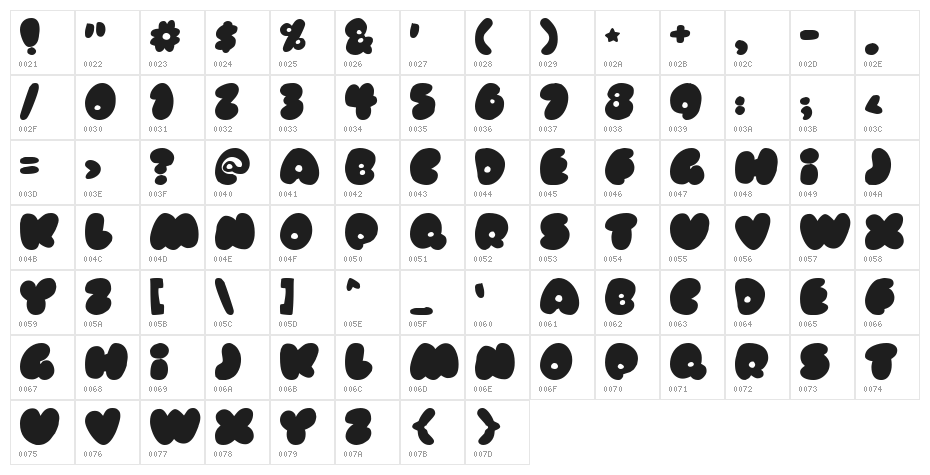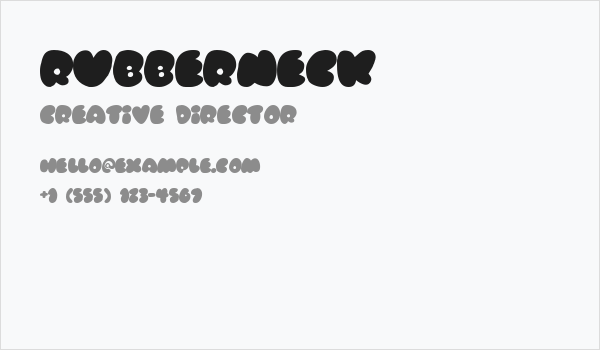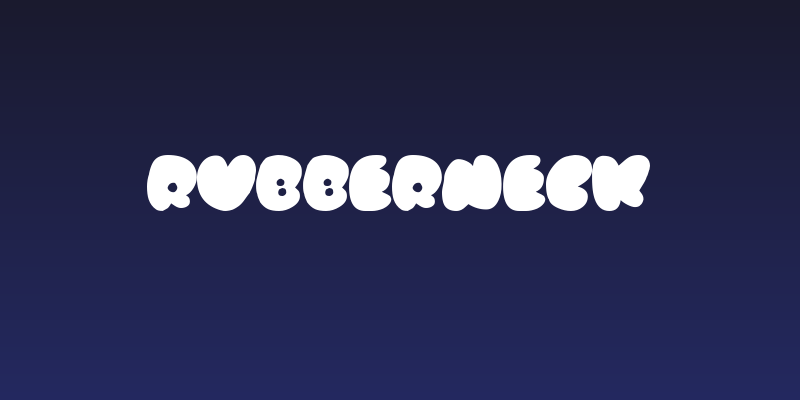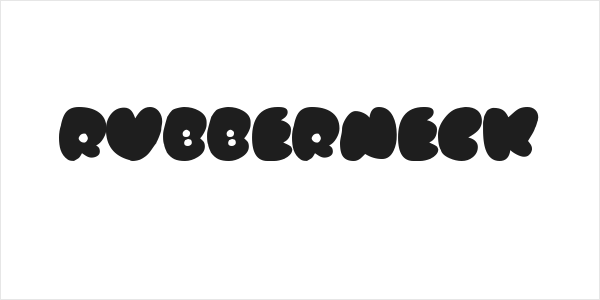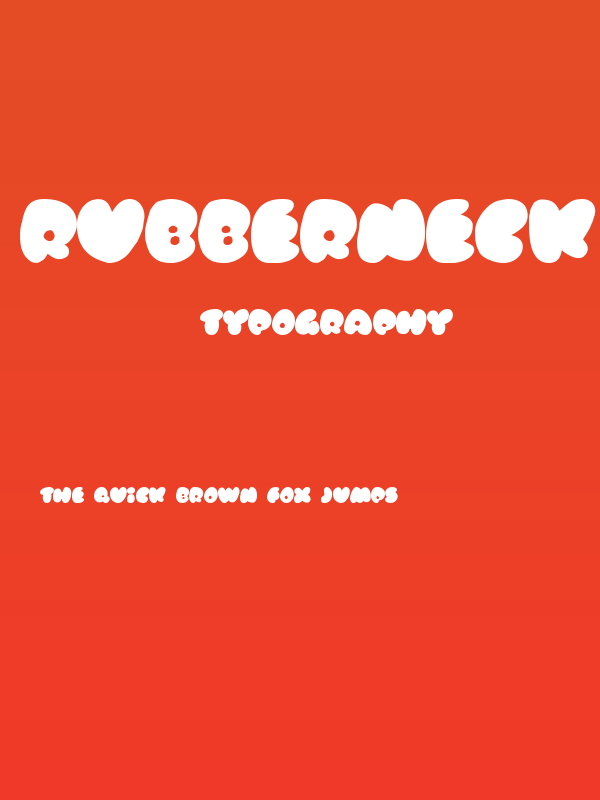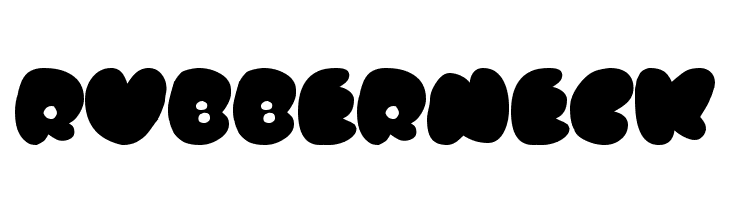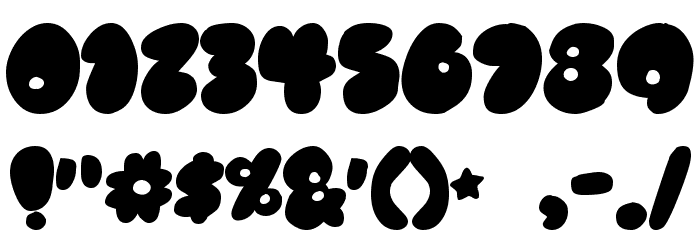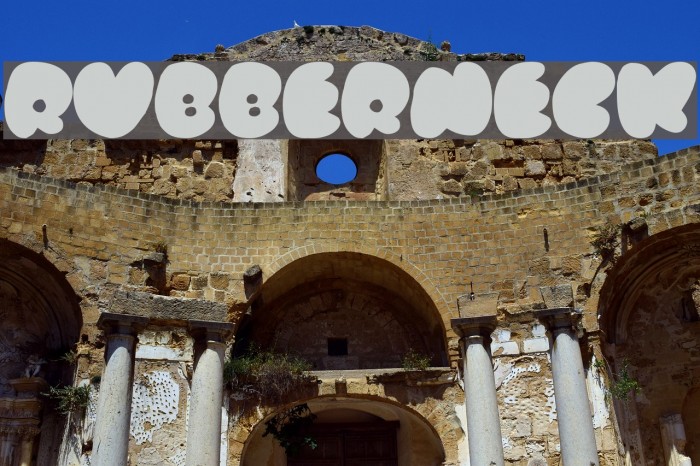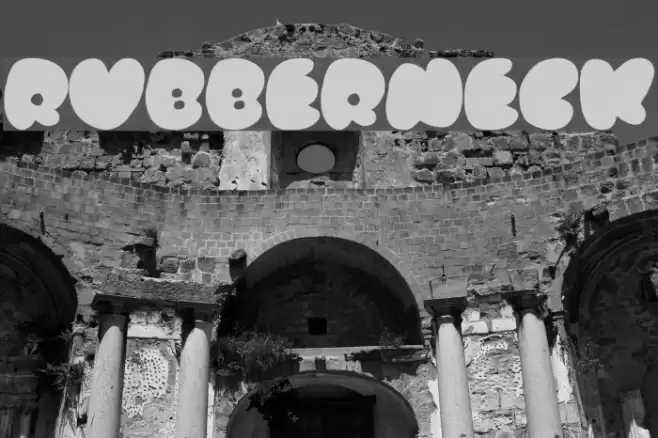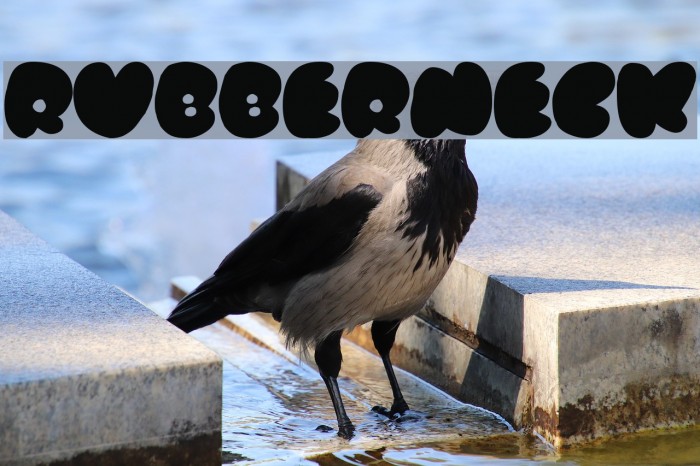
Rubberneck Font
| Breite | Expanded |
| Gesamtstil | Playful, Whimsical |
| Vorgeschlagene Projekte | Perfect for children's books, playful branding, party invitations, and any design needing a fun, informal touch. |